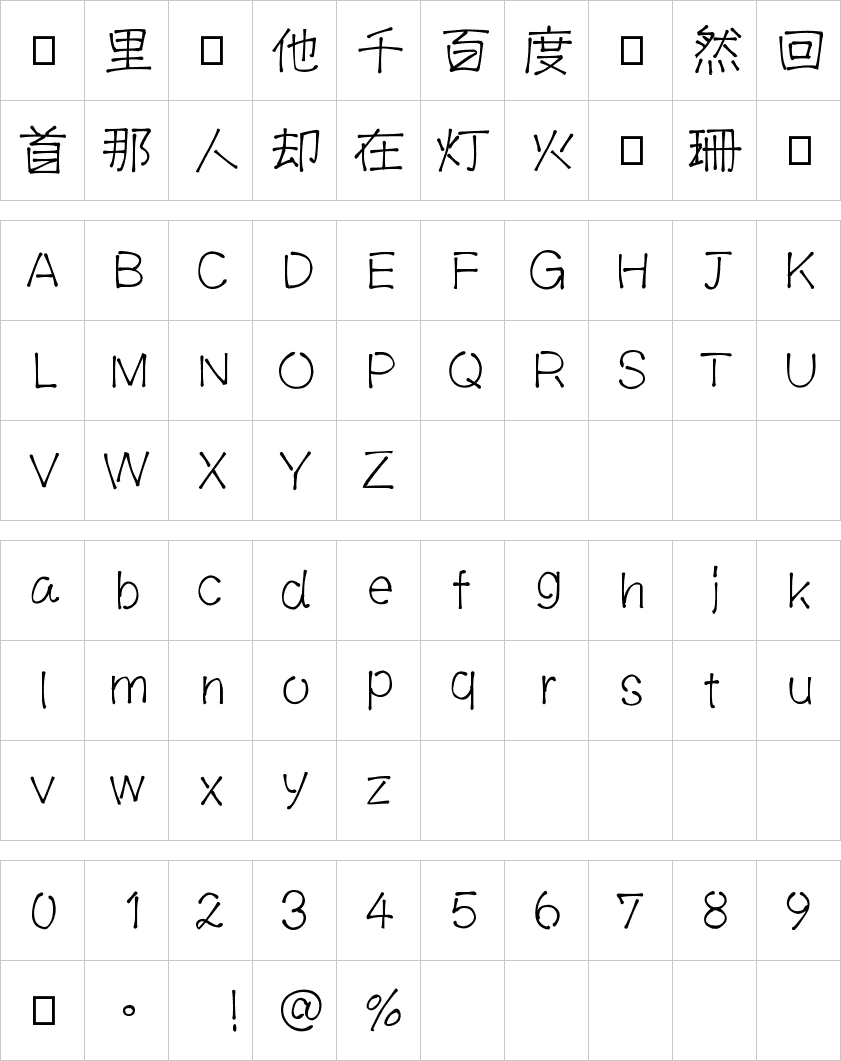
EbiharaNoKuseji
是横写用的手写字体。
我试着把经常被人说“像字体”的自己的字实际做成了字体。制作时使用的是iPad的应用程序“iFontMaker”。
因为用手习惯全开写的话平衡不好,所以以平时的手写文字为基础,注意尽量等宽。
推荐给喜欢像梅里奥那样宽幅大字体的人。但是,因为到处都有自己的习惯,所以请用样品图像确认气氛。
・这个字体不支持竖写
・推荐使用小一点的字体尺寸